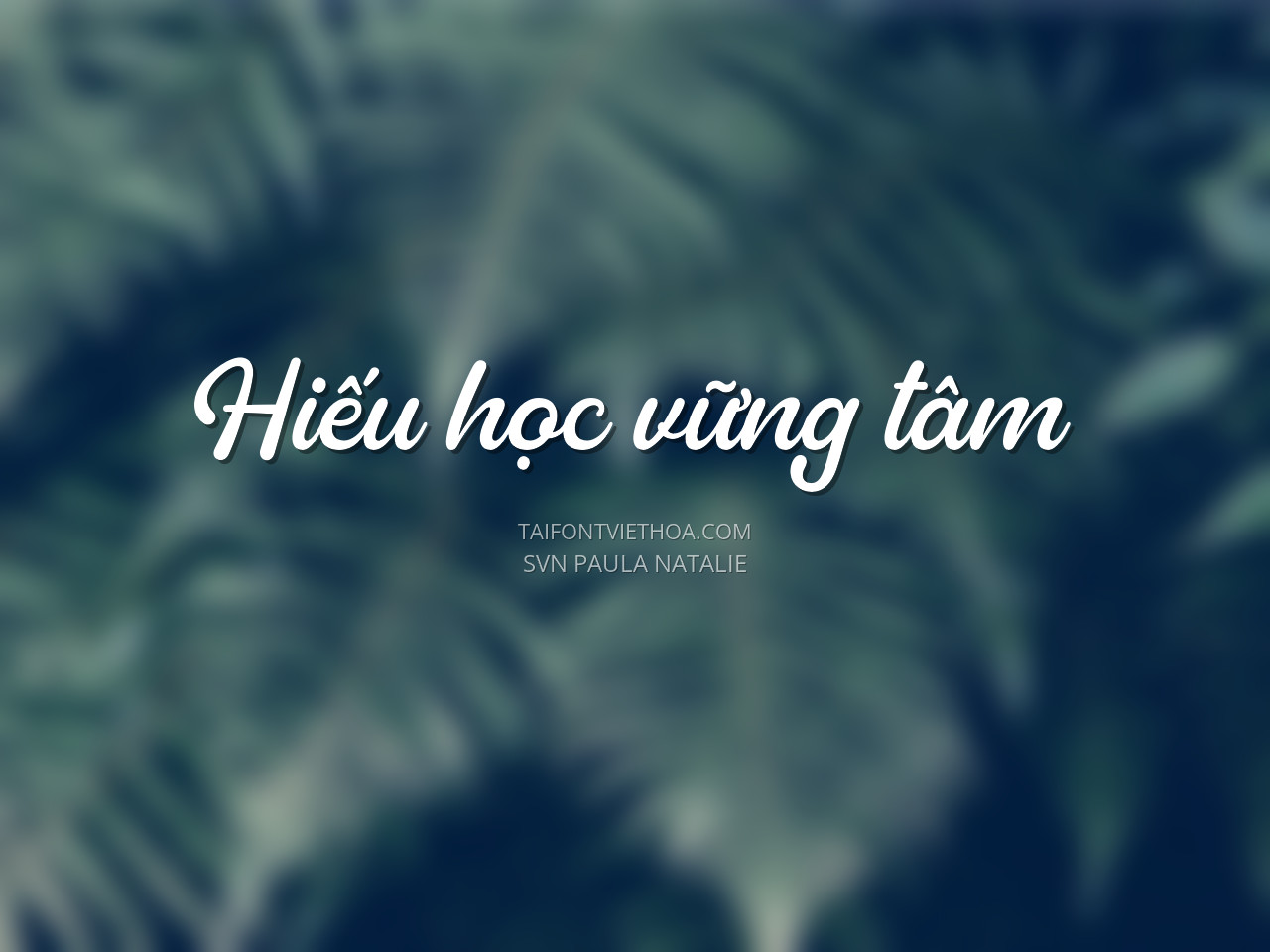
Font việt hóa SVN Paula Natalie
Giới thiệu về font SVN Paula Natalie – Kiểu chữ script nữ tính, thanh lịch và mềm mại
SVN Paula Natalie là phiên bản Việt hóa của font Paula Natalie – một kiểu chữ script mang phong cách viết tay tinh tế, nữ tính và duyên dáng. Font được thiết kế với những đường nét mềm mại, uyển chuyển, tạo cảm giác nhẹ nhàng và thanh lịch, rất phù hợp cho các dự án thiết kế thiệp cưới, bao bì mỹ phẩm hoặc thương hiệu thời trang cao cấp.
Phiên bản Việt hóa của SVN Paula Natalie được Taifontviethoa.comchăm sóc kỹ lưỡng, hỗ trợ đầy đủ dấu tiếng Việt cùng hơn 80 ngôn ngữ khác, giúp nhà thiết kế dễ dàng áp dụng trong các dự án sáng tạo tại Việt Nam, đặc biệt là trong lĩnh vực cưới hỏi, mỹ phẩm và các sản phẩm mang phong cách sang trọng, nữ tính.
Đường nét thanh thoát, mềm mại – Lý tưởng cho thiệp cưới và thương hiệu mỹ phẩm
SVN Paula Natalie sở hữu thiết kế script viết tay với các nét nối liền mượt mà, độ nghiêng nhẹ và các ligature tinh tế, tạo nên sự duyên dáng và sang trọng. Font mang lại cảm giác thân thiện nhưng không kém phần quý phái, rất phù hợp cho tiêu đề, logo, bao bì hoặc các phần thiết kế cần điểm nhấn mềm mại, bay bổng.
Ứng dụng lý tưởng: thiệp cưới, thiệp mời sự kiện, logo thương hiệu mỹ phẩm, bao bì sản phẩm cao cấp, bìa sách nghệ thuật, poster sự kiện và các dự án truyền thông cần phong cách tinh tế, nữ tính. Ngành nghề phù hợp: cưới hỏi, thời trang, mỹ phẩm, nghệ thuật, thiết kế sáng tạo và các thương hiệu định vị theo phong cách sang trọng, duyên dáng.